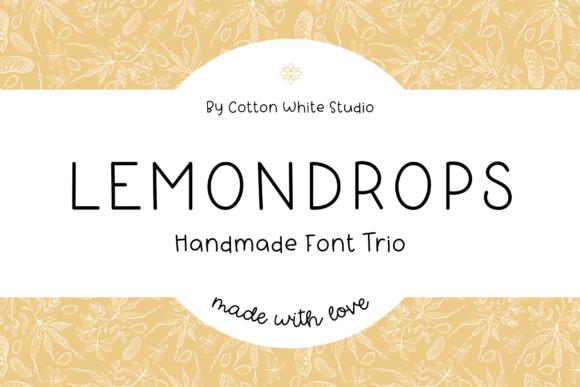
Lemondrops Trio
หากคุณกำลังมองหาเนื้อหาคุณภาพสูงเช่น Lemondrops Trio แพ็คเกจพรีเมียมนี้เป็นตัวเลือกที่ยอดเยี่ยมสำหรับโปรเจ็กต์สร้างสรรค์ของคุณ
สร้างขึ้นอย่างแม่นยำ Lemondrops Trio ให้เวกเตอร์ที่สะอาด พิมพ์ตัวอักษรที่ราบรื่น และใบอนุญาตเชิงพาณิชย์เพื่อความสบายใจ
ไม่ว่าคุณจะสร้างผลิตภัณฑ์ POD (Print on Demand) คำเชิญงานแต่งงาน หรือกราฟิกโซเชียลมีเดีย Lemondrops Trio ก็เหมาะสมอย่างยิ่ง